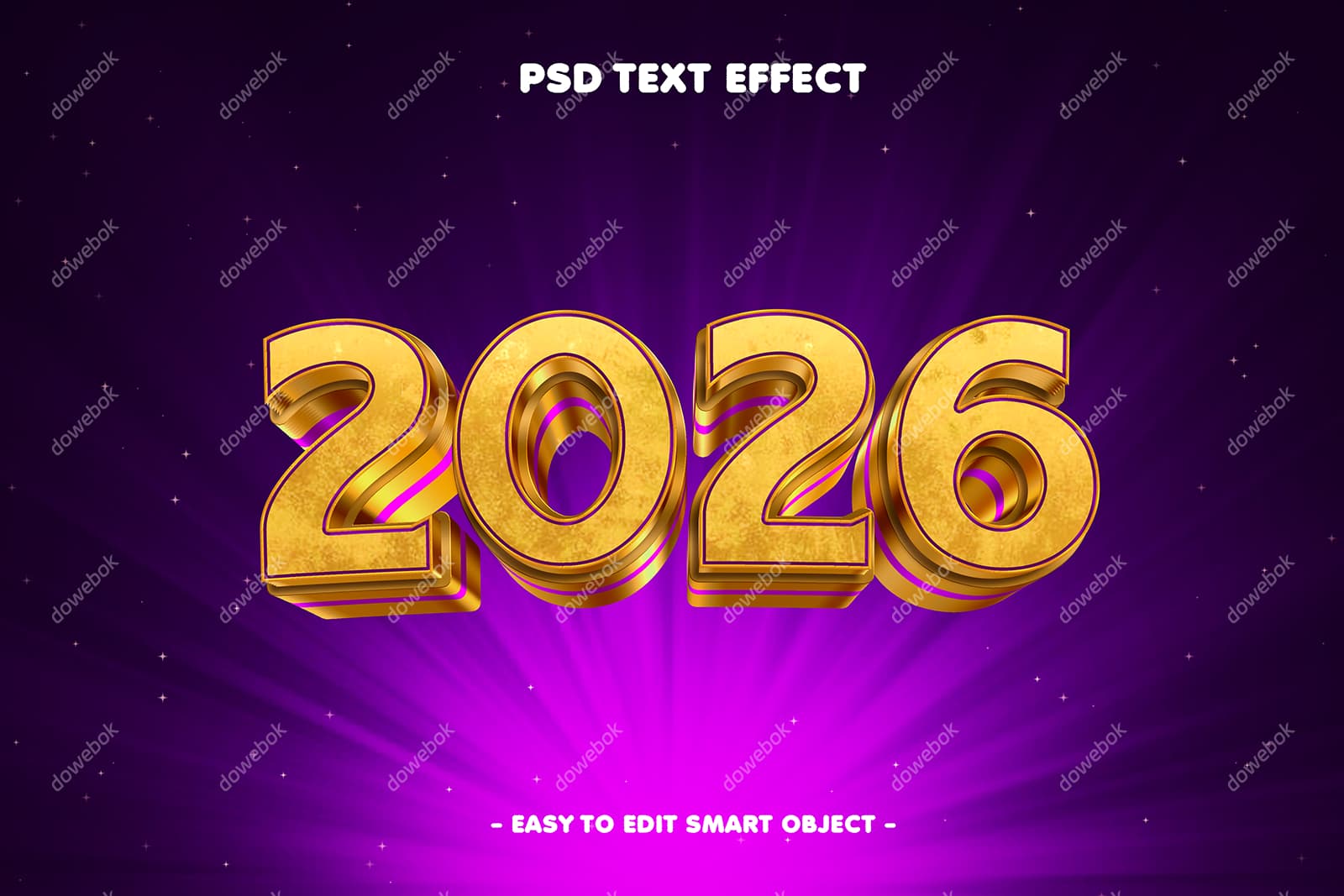
这是一款由金色立体数字设计的 2026 新年快乐背景素材,深紫星光背景衬着放射状紫光,“2026” 以鎏金立体字呈现,纹理精致且光泽感十足,上下标注 “PSD TEXT EFFECT”“EASY TO EDIT SMART OBJECT”。整体风格奢华闪耀,金紫配色既显高级质感,又借星光元素营造出梦幻氛围,既突出字体效果的精致性,也点明其可编辑属性,适配高端创意物料、装饰设计等场景。